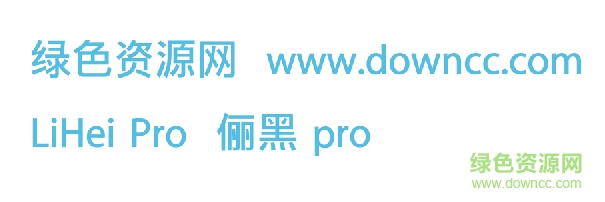
lihei pro字体又名丽(俪)黑pro字体。由苹果公司设计。小编为大家带来的是包含regular和Medium的版本。欢迎来绿色资源网下载!
lihei pro字体,中文名称又叫做丽黑pro字体,是苹果公司设计的一款非常实用的标准字体,该字体具有现代感的外观和清晰易读的效果,线条粗细适中,整体风格非常的出色,并且字库完整,可用于艺术设计、包装印刷、签名设计、图形设计等领域,有喜欢的朋友可免费下载收藏。
lihei pro简洁美观、优雅大方。